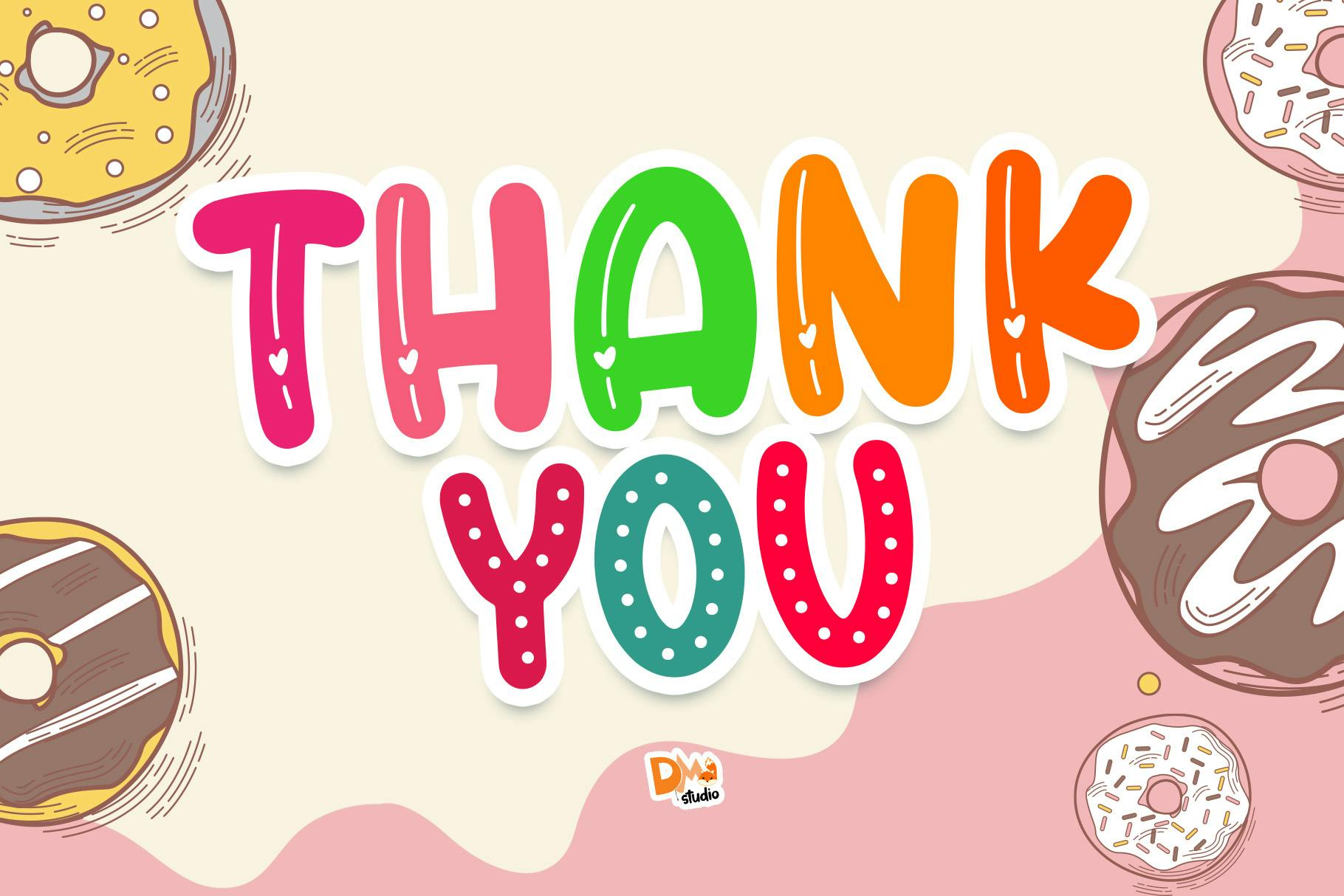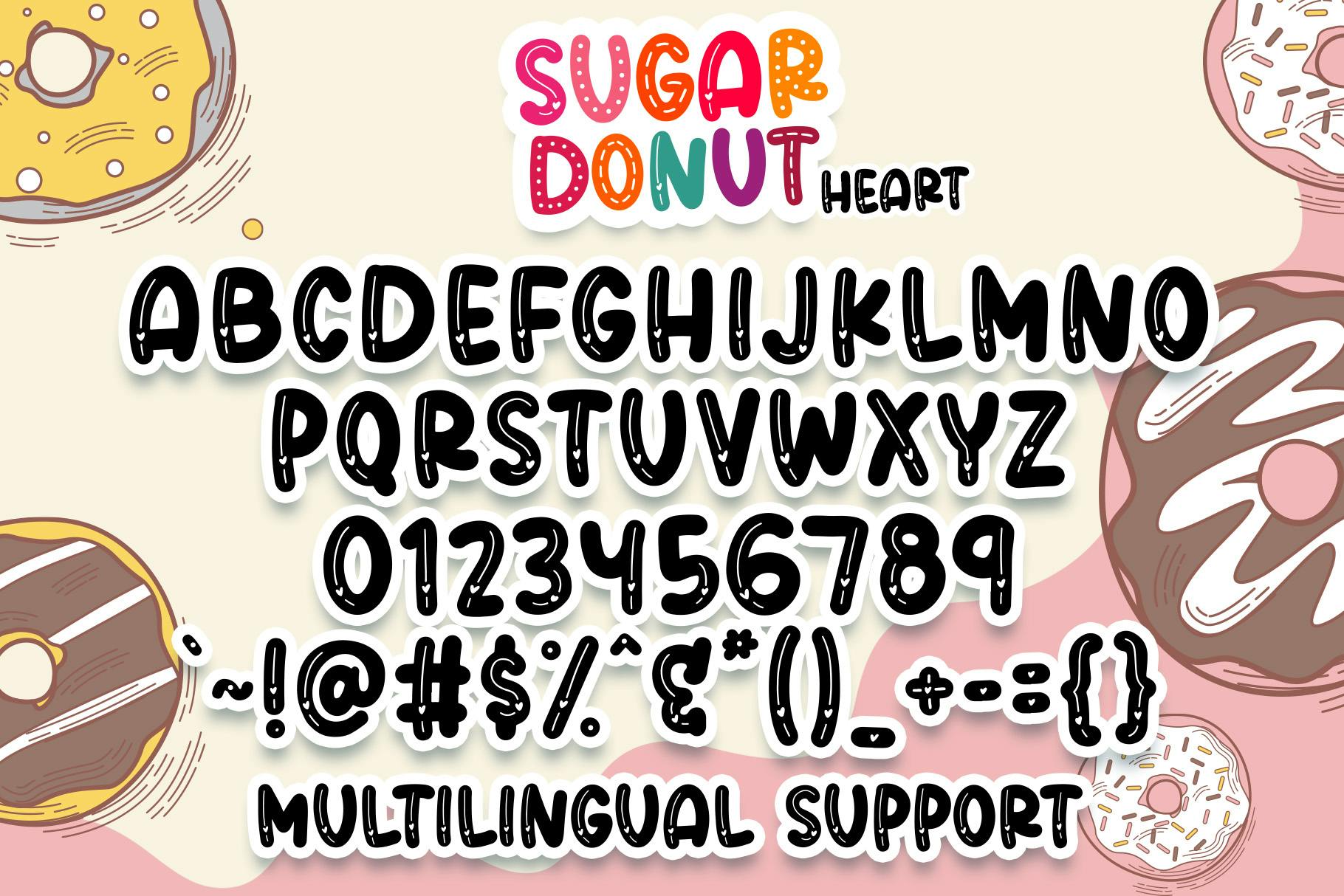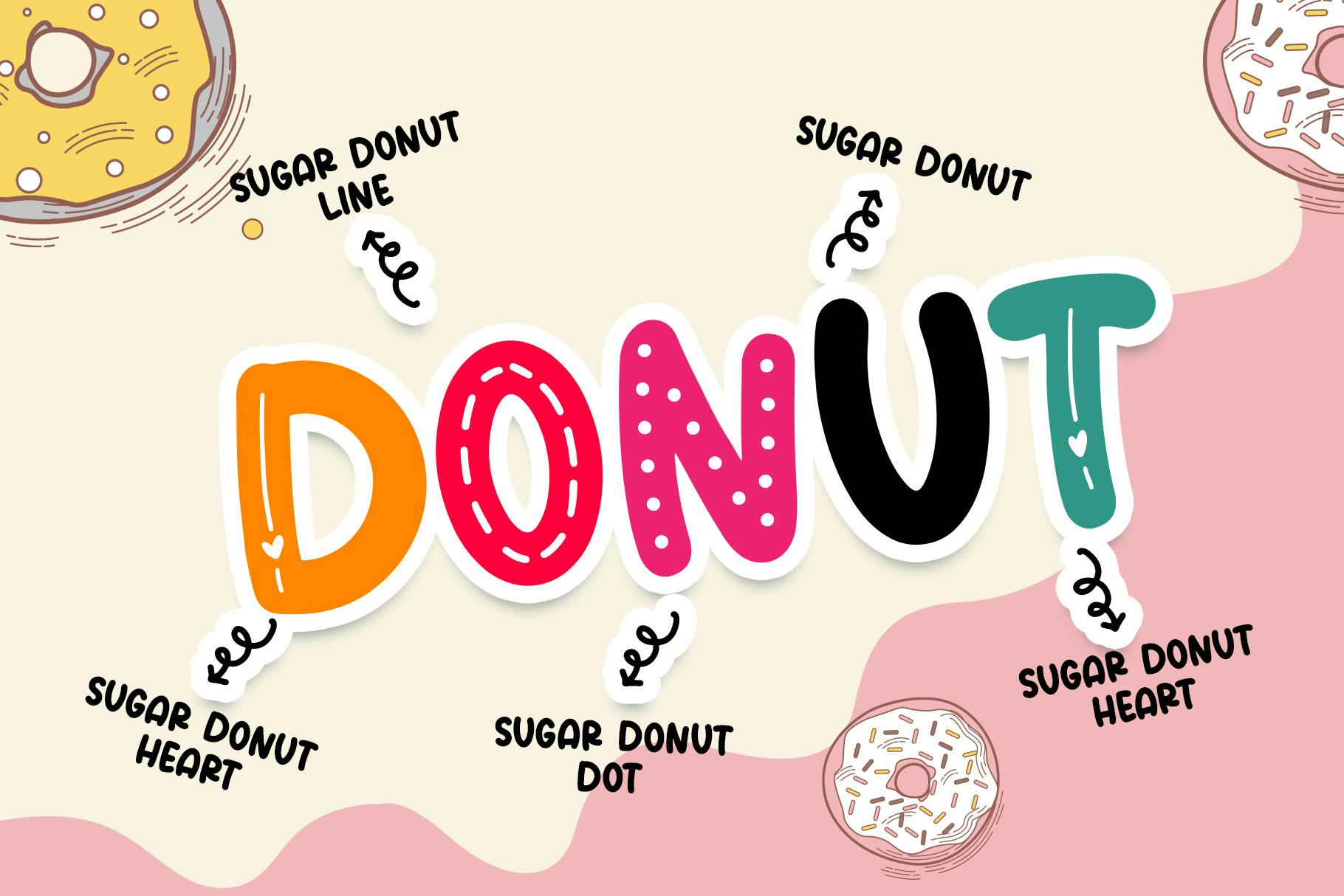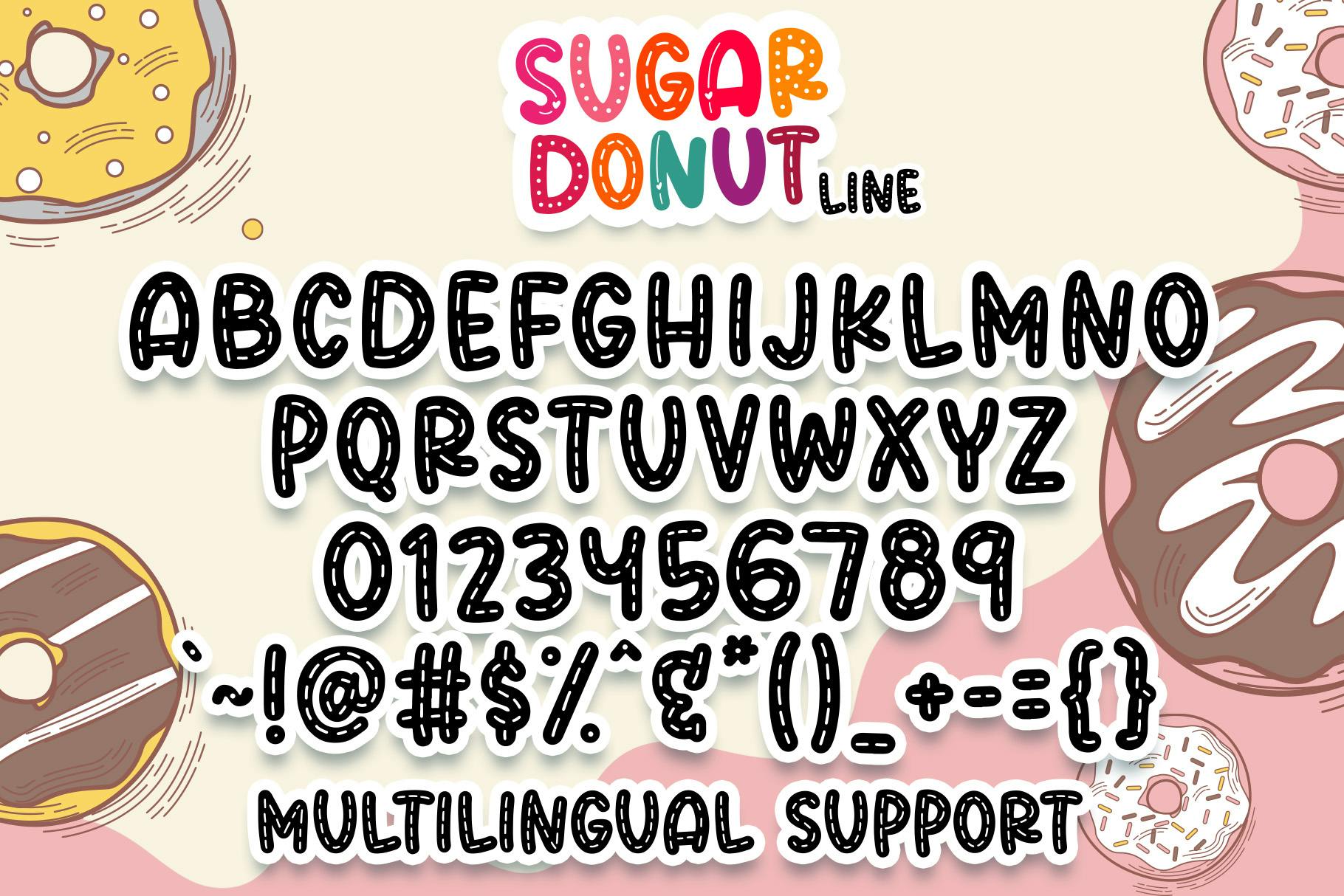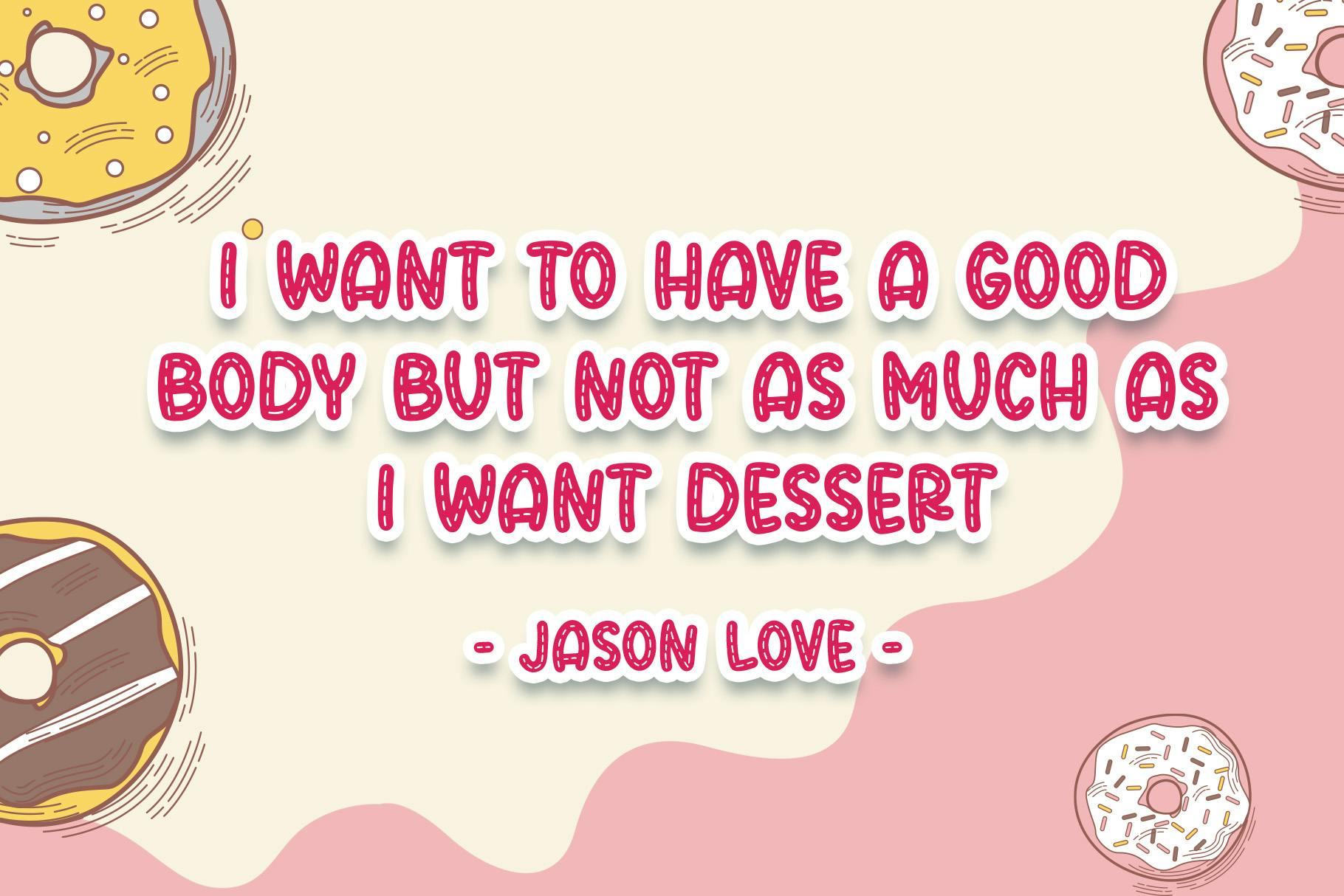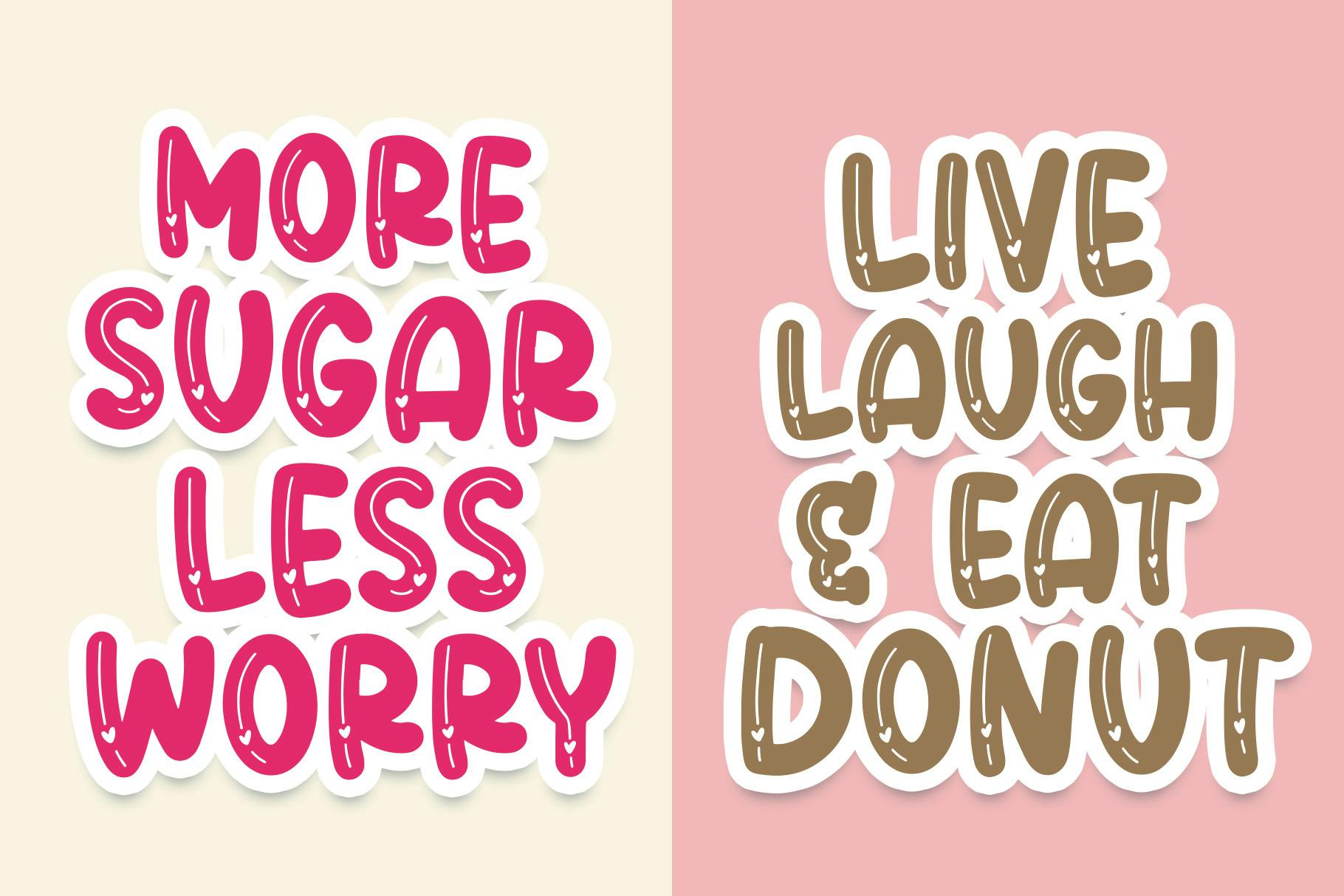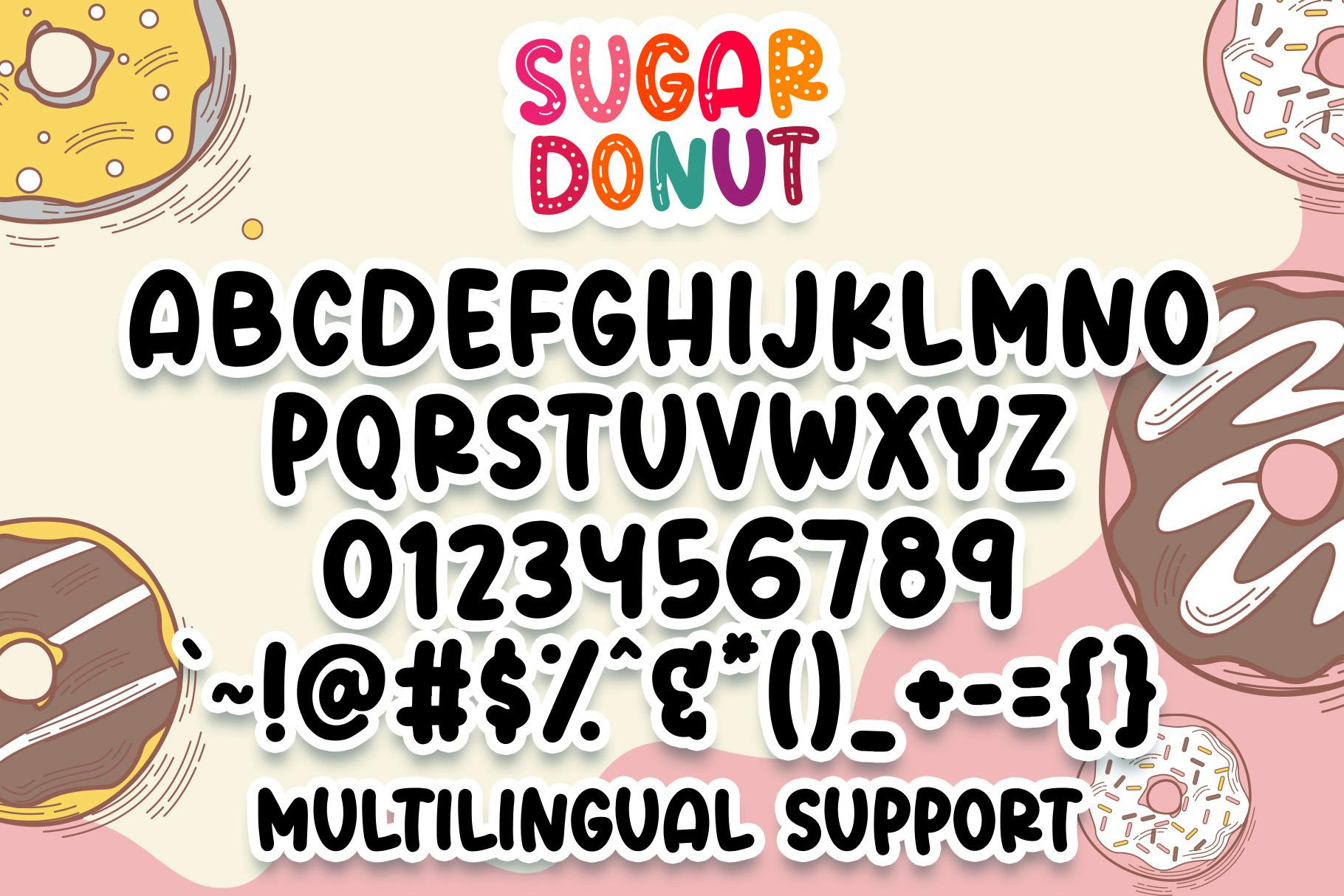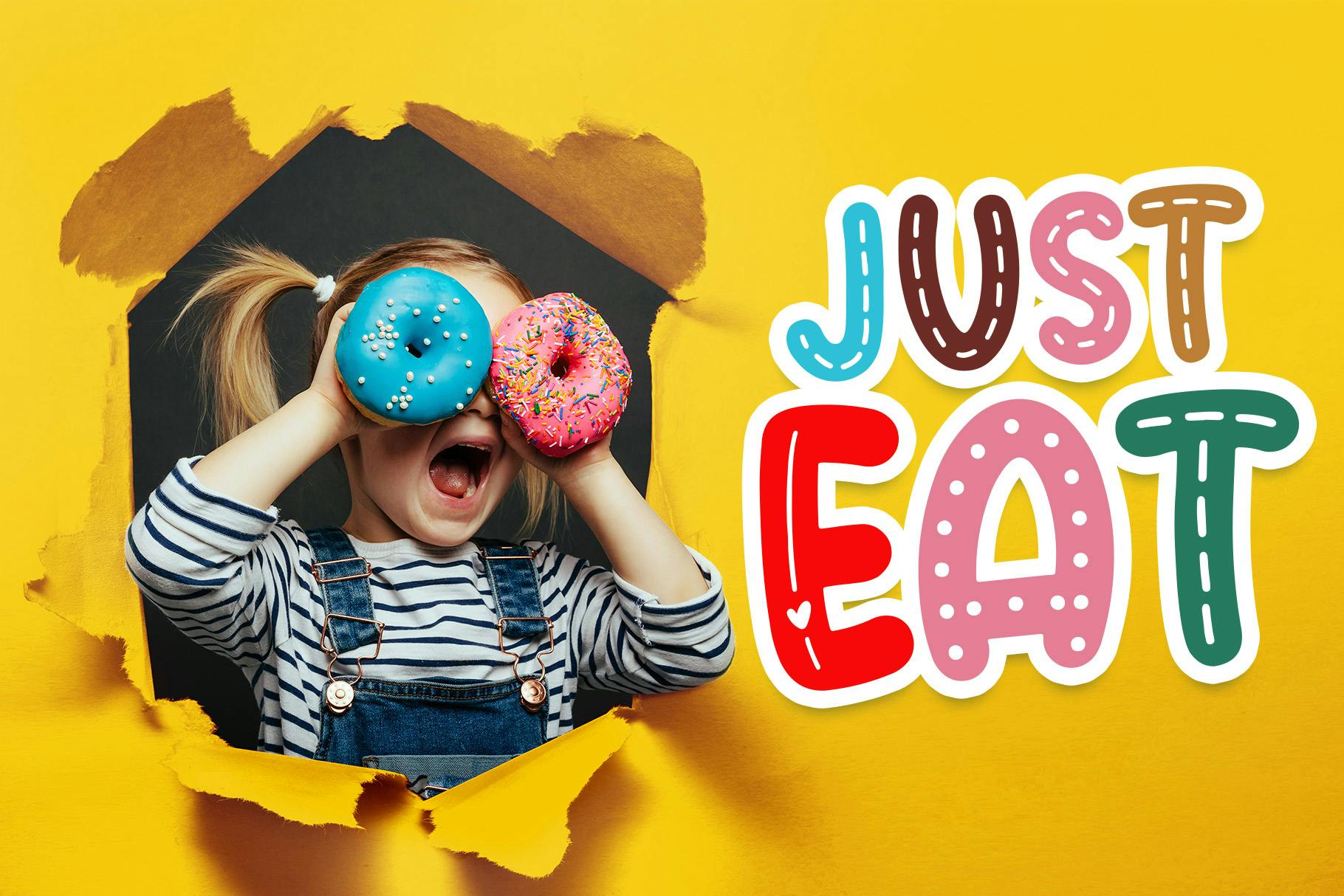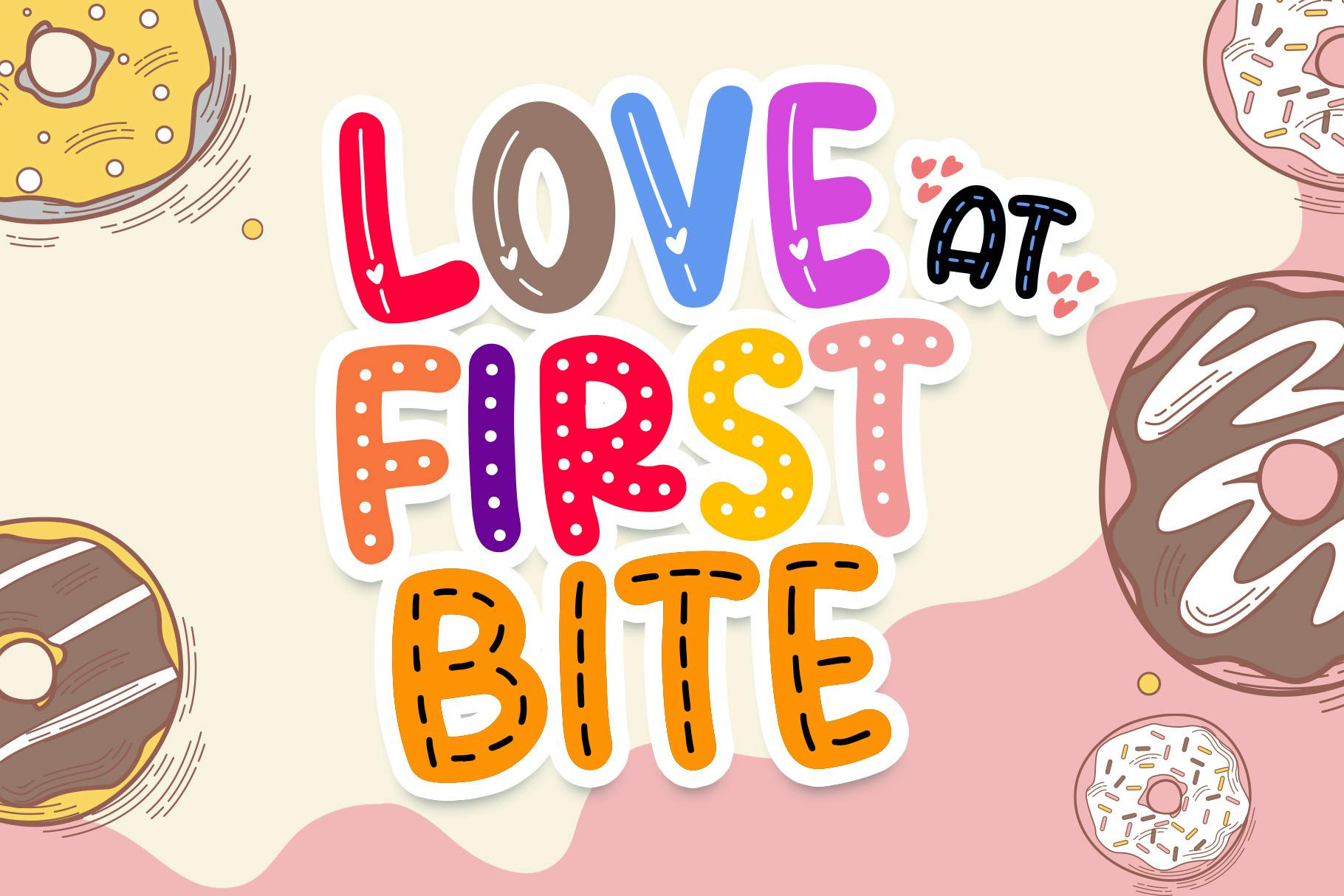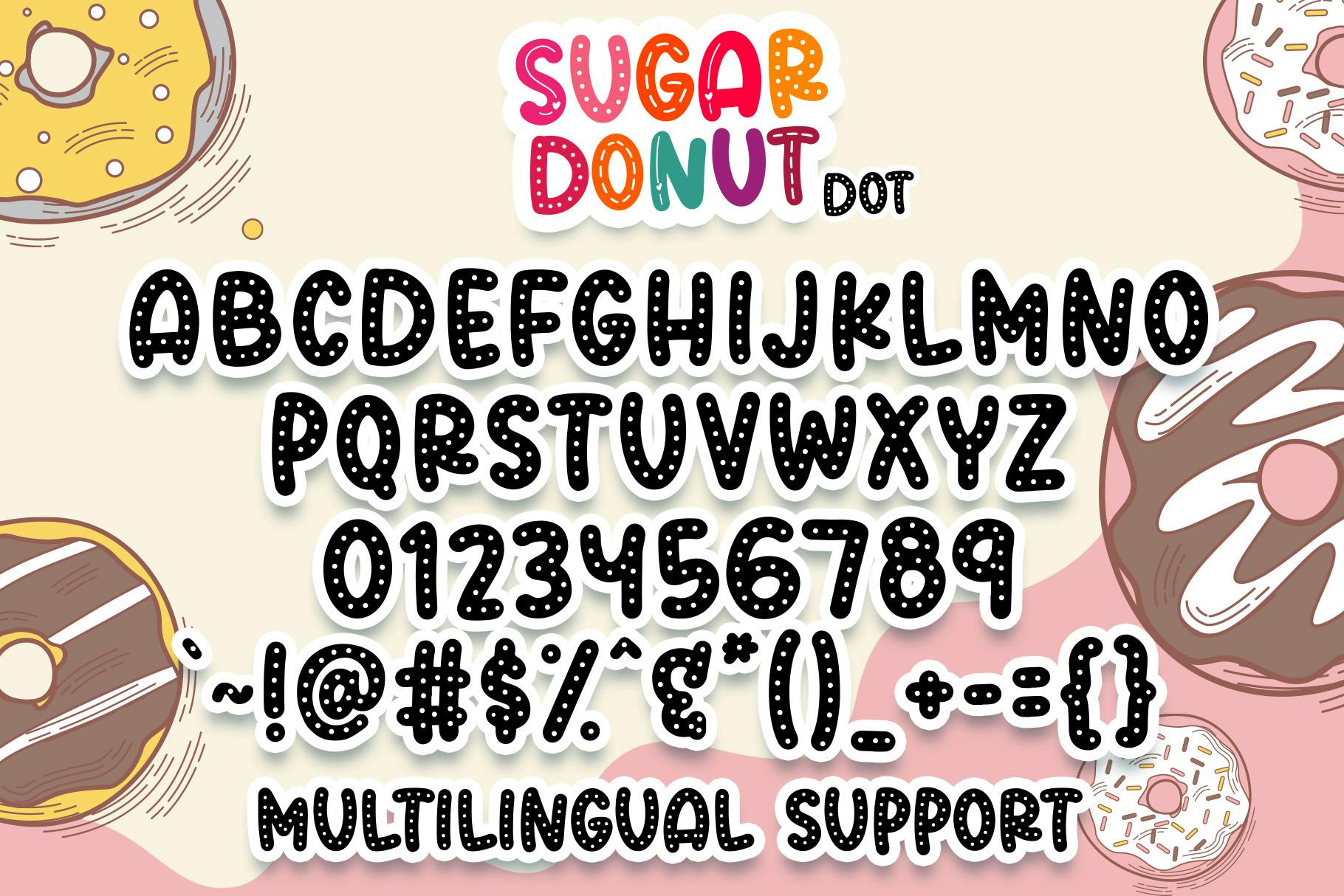
Sugar Donut Crafty Font
فونت Sugar Donut با طراحی دست‌نویس و شاداب، مناسب برای پروژه‌های شما.
فونت Sugar Donut، فونتی شیرین و خلاقانه است که به شما شادی می‌آورد.
این فونت ضخیم و دست‌نویس با تزئینات داخلی طراحی شده تا به پروژه‌های شما ویژگی‌های منحصر به فردی ببخشد. فونت Sugar Donut در ۴ سبک مختلف ارائه می‌شود که می‌توانید آن‌ها را ترکیب کنید یا به‌صورت مستقل در پروژه‌های خود استفاده نمایید!
ویژگی‌ها:
• همه حروف بزرگ
• ۴ سبک (عادی، دوخت خطی، نقطه، قلب)
• اعداد
• نمادها
• پشتیبانی چند زبانه